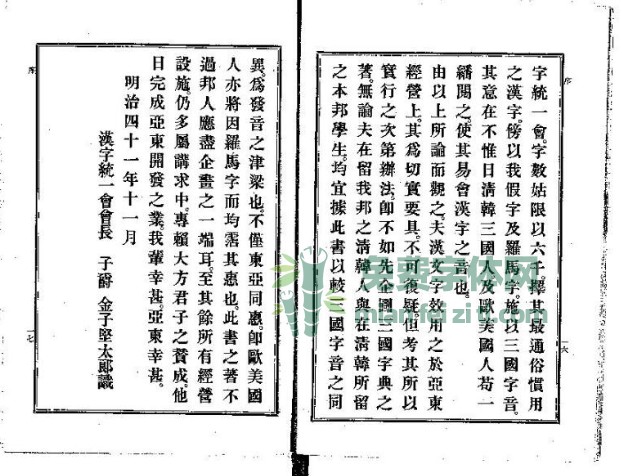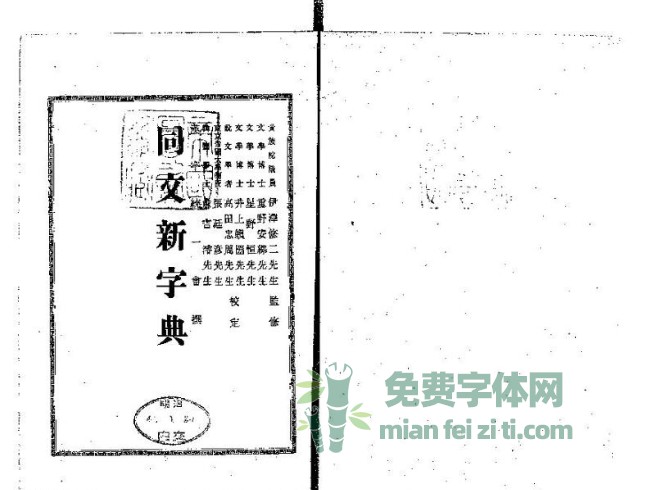
同文新字典体是从日本古籍《同文新字典》和《 [東京築地活版製造所]活版見本 》复刻而成的一款字体。这款字体的作者是日本的Yoshiki Hayashi,他在Github上建立了这款字体的开源项目,但是却没有提供直接的字体文件,只提供了std文件,要使用字体的话就要自己生成导出。
对于古典的复刻字体,之前免费字体网推荐过黄令东大神制作的《黄令东齐伋复刻》十分受到大家的喜爱及欢迎,现在的这款字体也是古籍字体复刻。不过免费字体网并没有找到更多的关于《同文新字典》的资料,这是日本明治年间的编著。
同文新字典体是一款古籍复刻字体,所以这款主要还是以繁体字为主,包括部分的简体字。